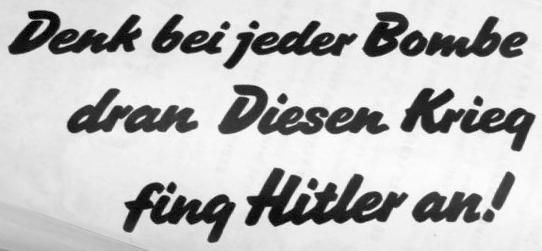
Suche Schrift dieses britischen Flugblattes von ca. 1940
die alliierten warfen Millionen von Flugblättern zu Propagandazwecken ab, u. a. eines dessen Schrift ich suche.
Das Flugblatt wurde ca. 1940 in England erstellt. Mir liegt nur die Rückseite mit dem Dreizeiler vor.
Kann jemand helfen, die Schriftart zu identifizieren oder ein Ähnliches zu finden? Die Alternative sollte kostenlos sein.
Wie man an dem von Ralf verlinkten Bild sehen kann, ist dies handgeschrieben und nicht gesetzt.
Nur annähernd ähnlich und kostenfrei (nur für den persönlichen, nicht kommerziellen Gebrauch):